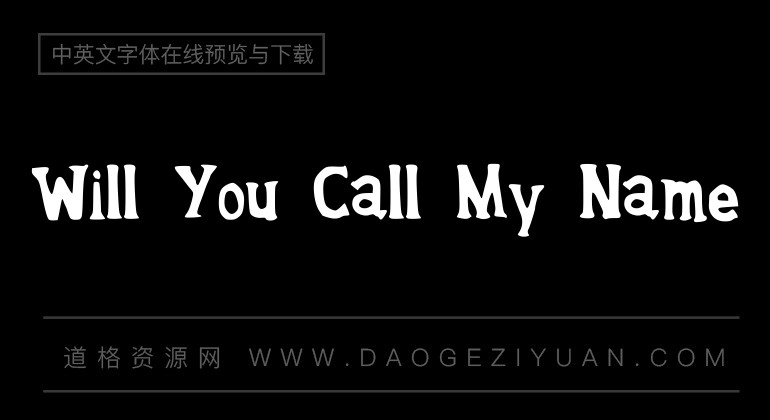
Will You Call My Name 是一款由 StudioTypo 创作的英文字体。它是一款时尚、现代、精致的英文字体,具有清晰的细节和优雅的外观。这款字体有三种不同的风格:细体、正体和粗体,可以满足不同的设计需求。它具有极高的可读性和可视性,适用于各种类型的文本,如广告、书籍、标签、标题等。内容介绍
Will You Call My Name是一款非常不错的手写艺术字体,具有很好的视觉感,适合于文化类的宣传设计、商业类品牌的广告和产品包装设计以及个性化文字排版等较多场景。